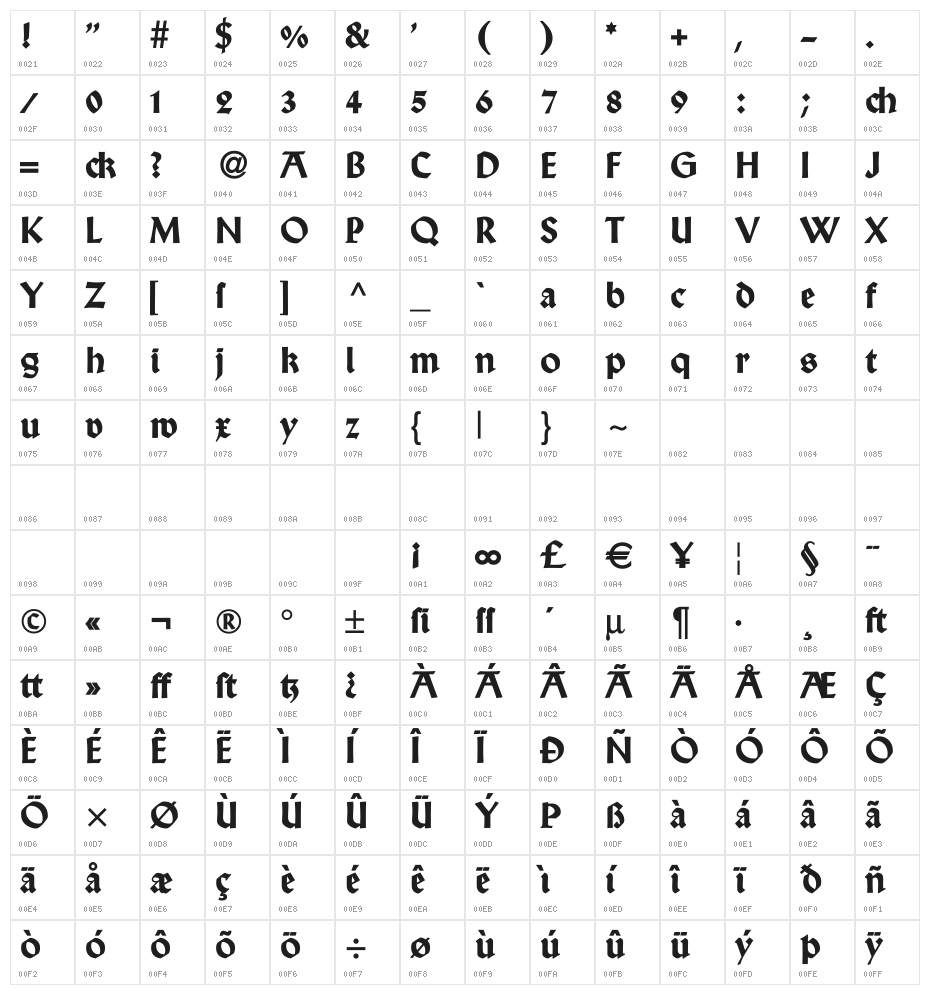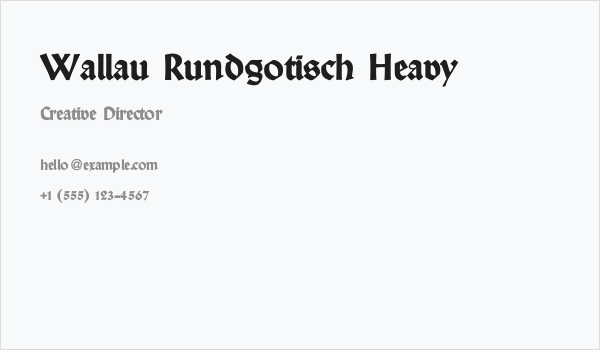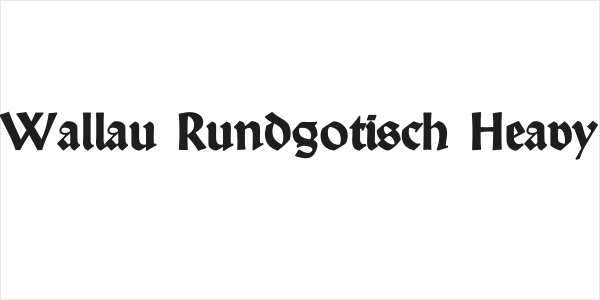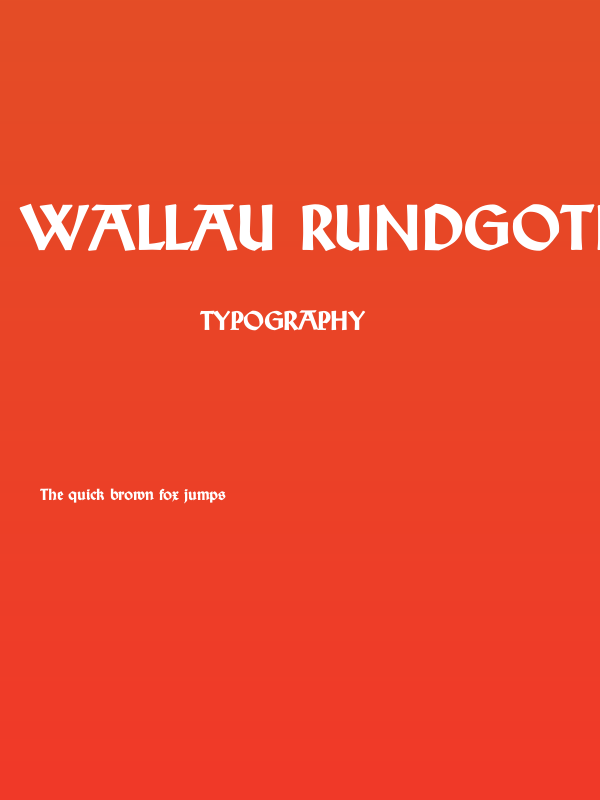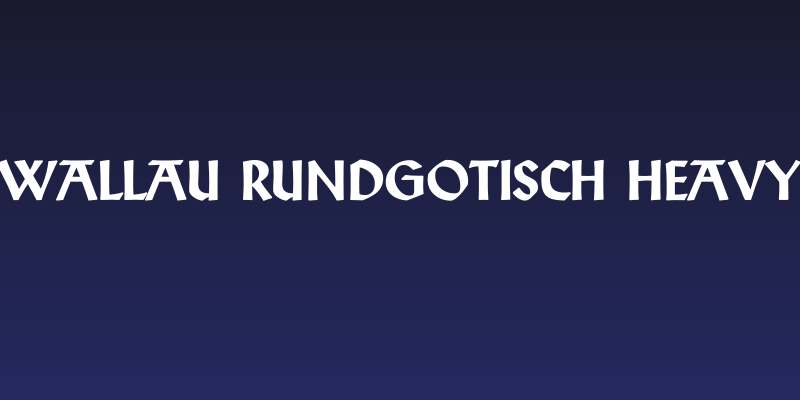
Wallau Rundgotisch Heavy Font
| Kategorien | Gothic |
| Gesamtstil | Classic |
| Anwendungsfall | Logos, Headlines, Certificates |
| Vorgeschlagene Projekte | Ideal for historical documents, certificates, branding for luxury products, or any design needing a traditional and authoritative feel. |